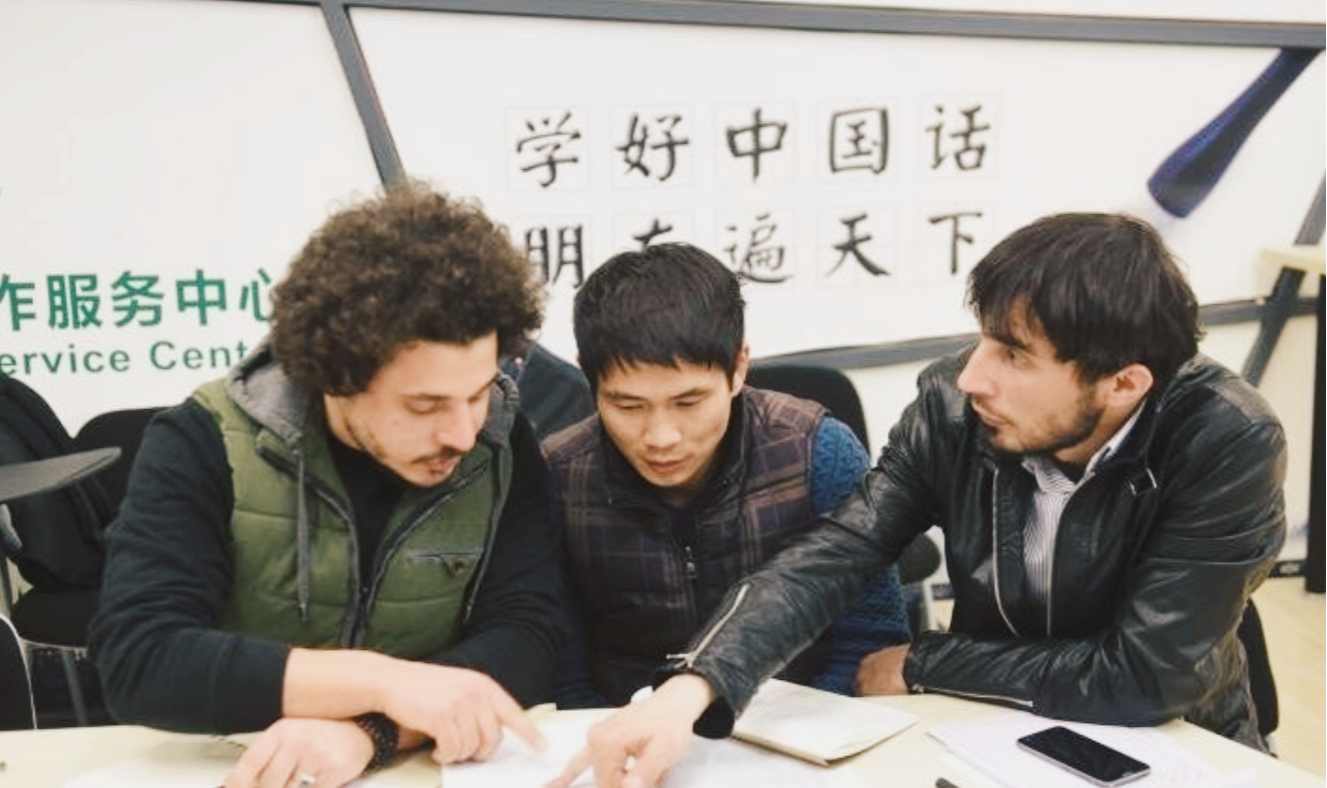
我国古代文化流传甚广,更是覆盖到了周边的很多国家,深刻地影响到了其他国家的文化发展,这一点甚至能够从文字上看出来。
我们的邻国韩国,虽然是已经有了自己的文字,但因为他们的文字是表音文字,所以他们的很多重要的典籍。
如法典一类的书籍,用的还是我们的汉字。
甚至他们的身份证上,除了韩语之外,后边也会有中文的名字,以方便进行辨认。
跟韩国不一样的是,日本是借用了我们的文字,并在此基础上,形成了一套独特的文字体系,既有文字,也有假名。
所以,日语中的很多东西,都是假名和汉字混用的。
但在安倍的墓碑上,却是连一点日语的痕迹都没有看到,全都是我们的汉字。
这又是什么原因呢?
墓碑上的字
日本首相安倍晋三,在演讲的时候遭遇了刺杀。
引起了世界范围内的广泛关注,在其去世不久之后,便按照日本的风俗习惯举办了葬礼。
每一个国家的葬礼形式都是不一样的,所以安倍晋三的葬礼完全是日式风格。
但随后人们发现,安倍晋三的墓碑上,竟然全都是我们的汉字。
他的墓碑上刻着“安倍家之墓”,虽说日语之中也有很多的汉字,但其实日本一般不会用“之”这个字。
相反,他们有专门的假名表达这个意思,就是“の”。
所以很明显,墓碑上刻的确确实实是汉字。
日语的变迁
其实日语深受汉语的影响,单单从其书写方式之中就能够看出来。
最开始的时候,日本完全没有使用文字的概念,毕竟我们已经建立起完全的封建君主专制的汉朝时,日本还是一个较为原始的社会,他们记录事件甚至还用打绳结的方式。
后来日本专门派遣人员前来学习我们的文化,因为他们本土完全没有文字,所以基本上就是照搬了我们的汉字过去。
但他们并没有经历文化的变迁,更不能很好的理解,每一个文字的本意和其延申意。
想要吃下如此庞大的汉字体系,对于完全没有接触过文字的日本人来说,太过于困难。
到了日本本土,在学习汉字的过程之中,他们也发现了这一点,所以将一些他们无法理解的复杂文字,进行了简化。
又延伸出了平假名和片假名,假名有自己的读音,同时汉字的音也用假名来标注,这样逐渐形成了自己的语言体系。
所以对于一个完全没有学过日语的人来说,一些简单的句子也能够轻易读懂,但发音却完全不会。
说到底,日语本质上,就是汉语到了日本延伸出来的产物。
甚至于他们的大多数外来语,也只能用假名标注读音的方式进行表示。
这也导致了一些外来语全用假名标注,看上去既不简洁,也容易混淆。
庄严尊重
时至今日,汉语的学习难度在世界上都是出名的。
像韩国这样的国家,很多人看上去对汉语不屑一顾,纷纷表示要用自己本国的语言。
可因为他们文字的局限性,一个音同样的写法,能有好几种意思,很容易混淆本来想要表述的意思。
所以,需要汉语来进行重要内容的记录,他们本土上还是会以自己会汉语为荣。
毕竟汉语的学习难度摆在这,需要深刻了解读音,声调以及汉字的书写,多音字,多义词等等。
比起韩国的表音文字,汉语不知道要难上多少。
能够学会汉语,是一件很厉害的事情,自然会受到尊重。
日本人也是这样认为,他们现在日语中的很多汉字还用的是繁体,尤其他们的文字是从汉字演变而来。
再加上,日本人派遣使节前来的时候,正好是隋唐时期,是国力最为鼎盛的时期,诞生出了无数美妙的文章,和脍炙人口的诗词歌赋。
其中的文学性让日本很多人心生向往,后来日本人在学习汉语的过程之中,也会因为自己能够念出这些诗词而感到自豪。
对于日本人而言,学习都已经是很困难的了,更别说自己写出这样的篇章。
只要能够说上一口汉语,自己也会写汉字,不用多问,一定是一些地位很高的学者。
所以日本也将汉语的地位看得很重,也跟韩国一样,十分敬佩那些会汉语的人。
在一些重要的场合,像重要的人物会面时用的横幅一类的,会场中只要是需要有文字表述的地方,用的也都是汉字。
甚至一些比较严肃庄严地方,像是什么佛堂寺庙之中,用的也全是汉字,所以对于日本人而言,汉字的严肃性要比日语高出很多。
这也就能解释为什么安倍晋三的墓碑上,刻的也是汉字了。
对于日本人而言,葬礼一样是需要庄严肃穆的场合,所以用汉字能够最大程度的表示出肃穆的感觉。
结语
我国的周边国家基本都会受到中国文化的影响,毕竟我们自古至今的文化,确实是一个宝库。
像我们的汉字,更是被我们看作是第五大发明,象形文字的魅力就在于此。
能够准确表述出意思的同时,留给了我们无数的想象空间。
很多时候,外语需要啰嗦进行表述的词句,汉语只需要用简简单单的一个成语,就能够准确表达出意思来,这也是其他文字无法比拟的。
而汉语的文学性更是突出,西方很难理解我们的文言文,以及各类文章的魅力,就是因为语言体系的不同。
日本一直是我们的模仿者,遣唐使前来不仅学习了我们的文化,还带回去了文字和佛教等等一系列他们当时本土并没有的东西。
并在当地本土化,形成了自己的一套体系,一直用到了现在。
如果没有汉语的存在,他们本身的日语能不能形成体系都是一个问题。
在他们的心中,还是对于汉语有一种敬畏心,不然也不会在那些庄重的场合,放弃使用日语,而是用汉语。